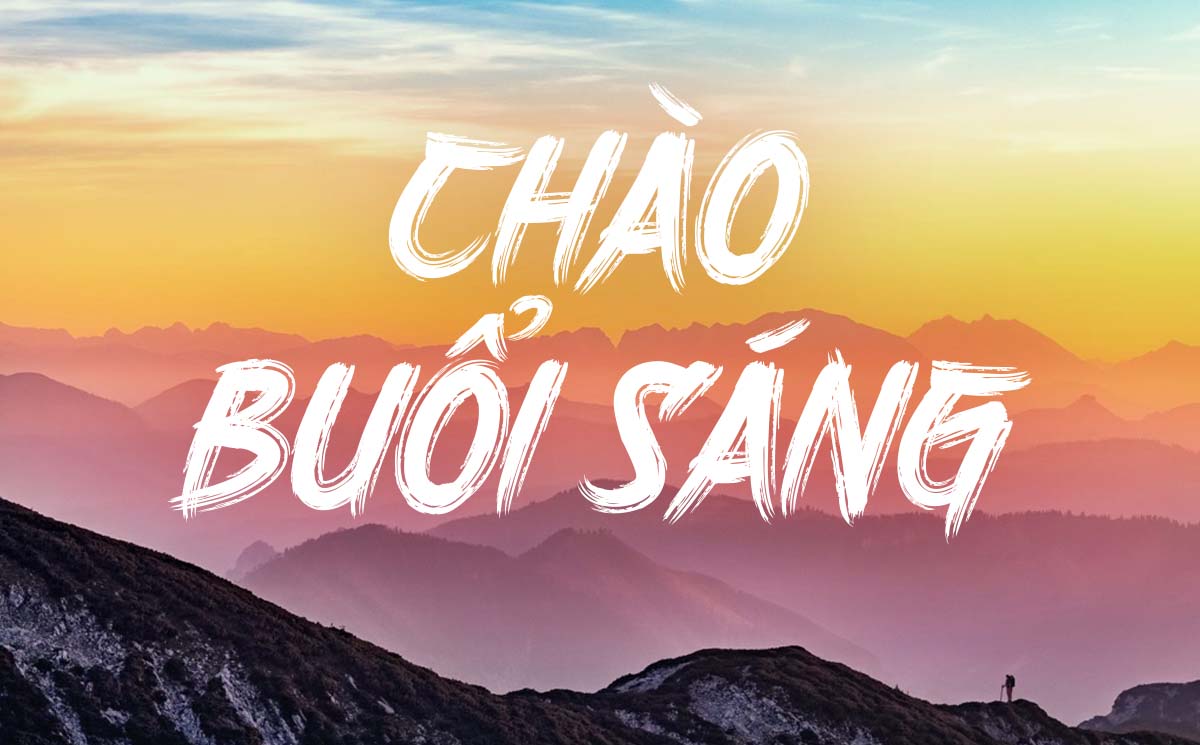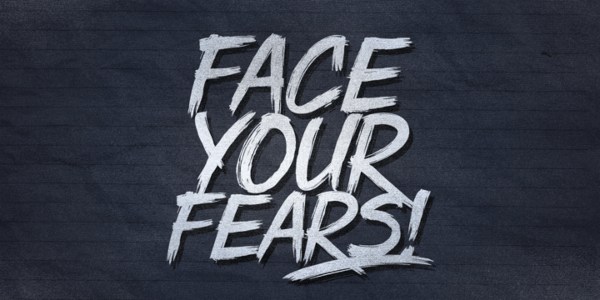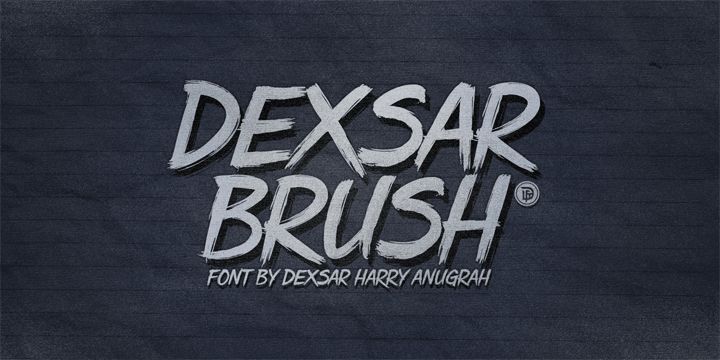
Font SVN DHF Dexsar Brush là gì?
SVN DHF Dexsar Brush là một phông chữ phong cách Brush Script đầy mạnh mẽ và cá tính, được thiết kế với các đường nét phóng khoáng như dùng cọ vẽ trực tiếp. Đây là lựa chọn phổ biến cho những bản thiết kế yêu cầu sự phá cách, năng động và có phần bụi bặm. Phông chữ này cực kỳ phù hợp để làm tiêu đề cho các poster sự kiện, nhãn dán sản phẩm dành cho giới trẻ hoặc các mẫu áo thun đồng phục độc đáo.
Đặc trưng của bộ chữ này là các nét xước tự nhiên (grunge texture) được lồng ghép tinh tế trong từng ký tự, tạo nên hiệu ứng thị giác mạnh mẽ. Tuy nhiên, bản gốc thường không hỗ trợ bảng mã tiếng Việt, gây khó khăn cho việc truyền tải thông điệp. Bản SVN DHF Dexsar Brush việt hóa tại In Viva đã được xử lý kỹ lưỡng các dấu thanh, đảm bảo độ cân đối và tính thẩm mỹ cao cho người dùng Việt.
Lưu ý: Khi sử dụng tải SVN DHF Dexsar Brush free để thiết kế in ấn, bạn nên kiểm tra kỹ các nét xước nhỏ. Nếu in trên chất liệu vải thô, các nét quá mảnh có thể không hiển thị rõ ràng.
Ứng dụng font SVN DHF Dexsar Brush trong thiết kế và in ấn
Nhờ phong cách đậm chất nghệ thuật đường phố, bộ phông này mang lại sự độc đáo cho nhiều loại ấn phẩm:
- Thiết kế bao bì và tem nhãn sản phẩm: SVN DHF Dexsar Brush việt hóa thường được dùng cho tên các thương hiệu nước uống, thực phẩm cay nóng hoặc đồ dùng thể thao, tạo cảm giác mạnh mẽ và kích thích thị giác.
- Sản xuất áo thun và nón: Các slogan cá tính sử dụng font này khi in chuyển nhiệt lên vải đạt độ sắc sảo cao, giúp món ấn phẩm cho doanh nghiệp trở nên thời thượng hơn.
- In ấn poster và banner quảng cáo: Những tiêu đề chương trình khuyến mãi sử dụng phông chữ này giúp thu hút sự chú ý nhanh chóng của khách hàng ngay từ cái nhìn đầu tiên.
- Gia công khắc laser hộp gỗ: Các đường nét của Dexsar Brush khi khắc chìm trên gỗ tạo ra hiệu ứng mộc mạc nhưng vô cùng tinh tế, phù hợp cho bìa sổ tay hoặc hộp trà gỗ cao cấp.